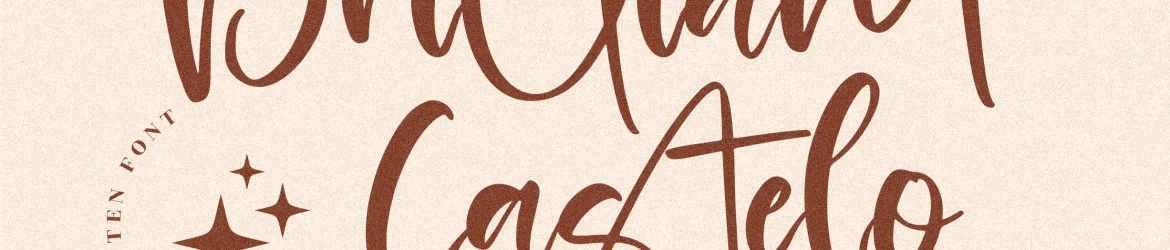
Brilliant Castelo Font – Download Grátis
Aqui está uma descrição criada para a página de download da font ‘Brilliant Castelo Font’, uma font escrita à mão adequada para diversas aplicações visuais: ‘Para designers, artistas e produtores digitais do Brasil, apresentamos a fonte Brilliant Castelo: uma opção perfeita para projetos que exigem um toque de autenticidade. Especialmente criada para logotipos, campanhas de marca, designs de mobiliário e embalagens, Brilliant Castelo é o ideal para qualquer projeto que precise de um sabor único de escrita à mão. Este conjunto de fontes foi projetado para oferecer uma variedade de opções, desde linhas mais suaves até formas emolduradas com traços exuberantes. Seja para criar um design para sua loja ou etiqueta, desenvolver uma identidade visual para seu produto, personalizar cartões de nome ou convites de aniversário, Brilliant Castelo oferece a solução perfeita. Estamos certos de que esta font será uma escolha agradável e prática para quem busca um toque autêntico em seus projetos. A sua versatilidade faz dela uma opção óbvia para qualquer projeto que exige um ar delicado, sofisticado ou artesanal. Brilliant Castelo foi criada pelo designer perspectype. Para os amantes de estilos à mão, este é o ideal para dar um toque pessoal aos seus projetos digitais. Adquira sua cópia agora e deixe-se envolver pela sofisticação da escrita à mão.’